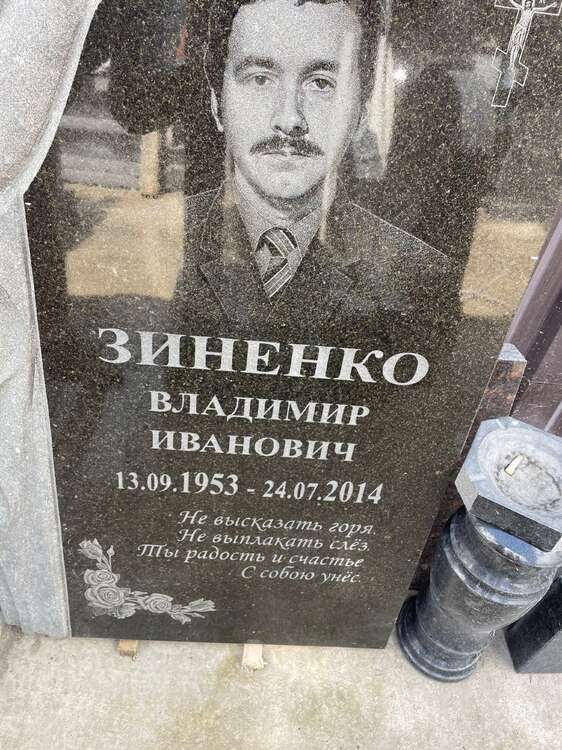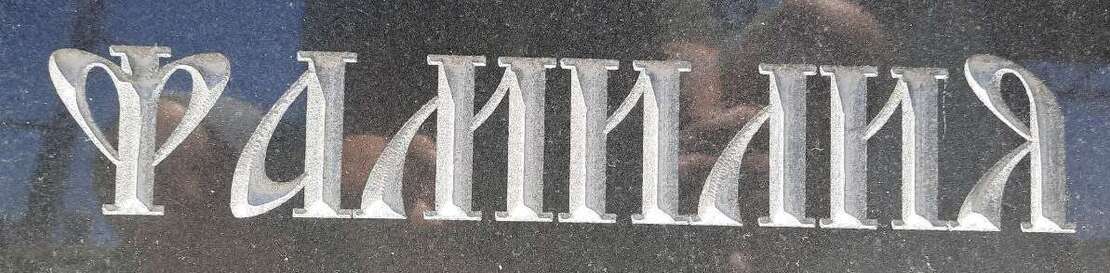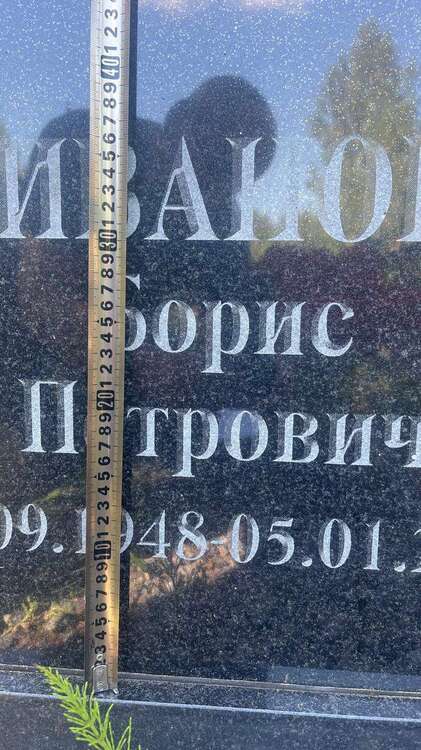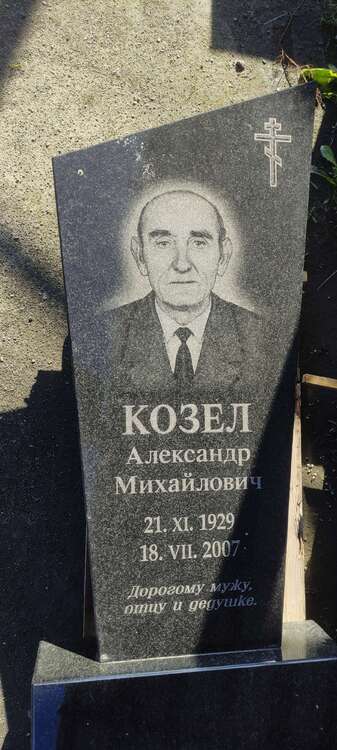
Помогите найти шрифт!
@kamishim Вот этот тоже близко Prosto Sans Bold
@Alexsey Ну, это совсем просто.....Times New Roman bold
@Art_em Это ручник, можно похожий найти.Фон сделать через наложение
@Art_em  Нашла только такие.....
Zapf ChanceC
Rhythm and Jazz Decor
Gabriela script
Adagio script
ArkonaC
Присматривался к шрифту Nautilus Pompilius, а потом сделал на основе классики Boyarsky. Заказчику еще не отправлял.
@Art_em Да, я посмотрела этот шрифт)) У меня его не было. Он лучше всего подходит))))) Вы молодец)
Всем привет, что за шрифт подскажите.... сам надпись резал- дупля отстрелить не могу....ХЕЛП МИ...
Это обычный шрифт из "таймов" просто немного теней наложили в фш.готовых для скачивания не видел таких.но вы сами сможете его сделать https://creativo.one/lessons/text/1015-otlivaem-tekst-iz-zolota-v-fotoshop.html
Подскажите, пожалуйста, шрифт
@SKt Перелопатила  все, что можно...... Азарт словила, но ничего не нашла.........
@алена :girl_dance:. В Телеграмм в чате про шрифты видела похожий. Пошукала, точно вроде он.
все мпривет. может кто знает такой шрифт?
@den-by Times New Roman
Всем привет, что за шрифт подскажите....
Помогите найти шрифт эпитафии, пожалуйста.